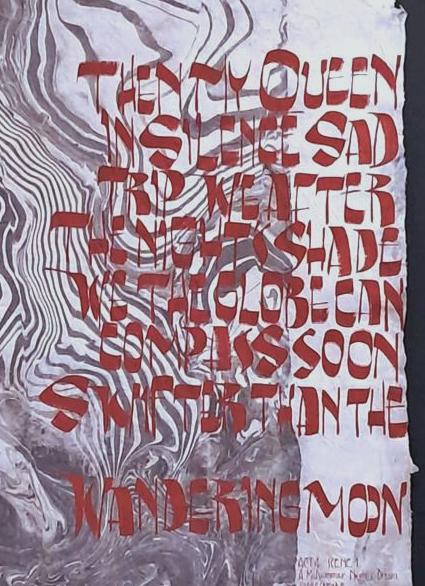
"Le geste humain", un stage de Monica Dengo
J'ai passé le week-end du 1er mai à Paris pour assister à un stage organisé par l'association Barbedor. Leur invitée était Monica Dengo, une calligraphe italienne de renommée internationale.
Le thème du stage était "Carnets d'artistes, le geste humain ". Je suis cette artiste sur la toile depuis longtemps et je suis charmée par l'énergie à la fois brute et maîtrisée de ses graphismes, par leur harmonie et leur énergie, par la justesse des équilibres vide/plein et par leur puissance élégante.
Nous avons commencé par nous interroger sur la graphie manuscrite versus l'imprimé, soit la main, le geste d'un tracé unique versus la machine qui copie en de nombreux exemplaires un écrit. La machine reproduit quand la main trace, produit un écrit unique dans le temps et l'espace. Comment la calligraphie se positionne-t-elle par rapport à cette dialectique ? Y a-t-il une pratique alternative, qui rend compte du geste humain de manière plus intime que la calligraphie ? Qui quitte le lisible tout en étant porteur de signification et le résultat d'une réflexion esthétique ? De là nous avons exploré la dimension lisible/illisible de l'écriture manuelle quand écrire ne se donne pas pour but la lisibilité et que des champs graphiques s'offrent à la main.
Nous avons utilisé des outils scripteurs en recherchant leurs possibilités de production de traces : le pinceau plat puis un outil que nous avons choisi. J'ai utilisé un petit colapen triangulaire de ma fabrication. J'ai créé un répertoire de traces puis j'ai sélectionné celles dont la forme évoquaient des lettres J'ai modifié ma façon de tenir l'outil, j'ai l'ai pris par le bout de son manche, en lâchant ainsi une part relative de maîtrise sur l'outil. Les traces, lignes et traits ainsi produits ont été en partie conduits par mes intentions auxquelles se sont mêlés le poids, le pivot, des résistances aléatoires...d'un outil moins soumis que d'habitude. Après la réalisation d'un alphabet, j'ai écrit quelques mots puis un haïku de Basho dont je n'ai gardé qu'un mot, "grenouille". Je savais que je voudrais poser mes lignes personnelles, mes cheminements. La grenouille se déplace, les longues jambes sont des traits brisés, sa langue se projette en une ligne droite et les formes de ses lettres contiennent à la fois la droite, l'oblique et le cercle, soit les traits de base de notre alphabet latin. Monica nous a donné comme consigne d'écrire notre mot en cercle, les lettres étaient là mais non lisibles d'emblée. Et puis on a introduit de la couleur, j'ai utilisé de la gouache dorée, et je me suis laissée aller au plaisir de la trace, de la calligraphie abstraite, du contour, de la matière, des effets de présence, des collisions. Trois livrets sont cousus sur une bande de papier de couverture à quatre plats avec donc des ouvertures de pages qui se superposent. Chaque feuilletage du livre est un parcours unique plus ou moins aléatoire.
Monica a présenté nos livres en volumes en coinçant les pages dans les plis, comme des sculptures de papier.
le colophon du livre
Linocalli - Lascia la spina
J'ai animé récemment un deuxième stage Linocalli à Lugano dans le Tessin. Vous voyez ci-contre le tableau que j'ai réalisé tout au long du stage en démonstration.
Comme le Tessin est un canton de la Suisse où l'on parle italien, j'ai choisi un extrait d'un lied de Haendel, "Lascia la spina, cogli la rosa". Sur mon compte Instagram j'ai choisi l'interprétation de Philippe Jaroussky comme accompagnement musical. La version de Céliclia Bartoli est aussi très belle.
Nous avons commencé par calligraphier le texte au colapen puis il a été reporté sur du calque et transféré sur une plaque de lino. Est venue l'étape de la gravure puis l'impression. Nous avons imprimé sans presse, au rouleau avec de l'acrylique et au baren avec une encre typo sur du papier fin. Ci-contre, j'ai collé un tirage à l'acrylique rouge, que j'ai ensuite voilé d'une feuille de papier fin. "La spina" est calligraphié à la plume carrée, "Haendel" à la plume J et "Lascia" est posé en gestuelle au colapen. La lettre linogravée, calligraphiée posément à la plume carrée ou lâchée dans une série de gestes vifs se glisse à différents niveaux de présence, de profondeur. S'y ajoute le plaisir du pigment rouge qui s'épanouit sur le grain du papier fin.
Diemensions : 25 x 21 cm
Quelques détails :
Je pense mettre ce stage à mon programme de l'année prochaine.
Lettre Art Nouveau au pinceau pointu
LETTRE ART NOUVEAU AU PINCEAU POINTU
Atelier de Kervoulouarn
Le pinceau pointu, travaillé en souplesse et appui se prête je dirais naturellement, aux formes organiques et végétales de l'art nouveau.
Suite à une demande, j'ai ouvert un stage de deux jours à mon atelier sur le travail de la lettre art nouveau au pinceau pointu.
Nous partirons des formes de la Secession viennoise de la revue Ver Sacrum. Nous les tracerons en premier lieu au pinceau pointu en jouant des qualités physiques  de l'outil et dans une seconde approche en sculptant la lettre à partir d'un modèle de MIG.
Nous exposerons le tableau ci-contre, Then my Queen, et une série de petits formats calligraphiés : Gris galets, Si près de la cité, Ma précieuse, Vue brouillée, Bonzaï, Epinglé et Le clou.